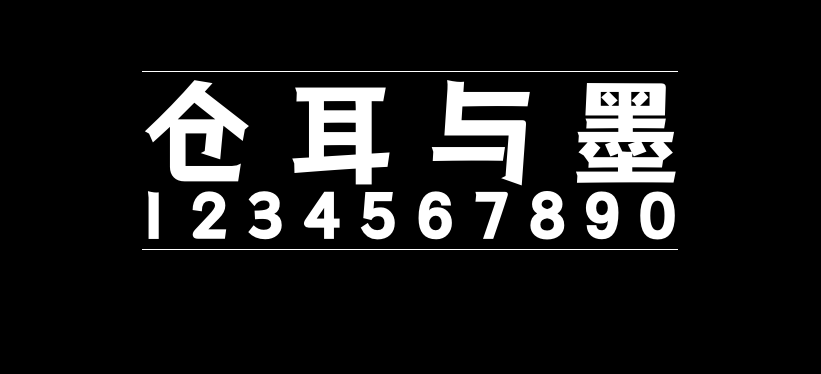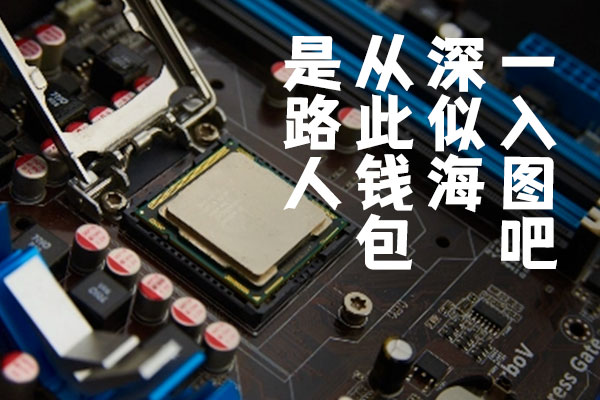
仓耳与墨
仓耳与墨(TsangerYuMo)是仓耳字库推出的一款免费字体,该字体包含5个字重,风格偏向现代创意字体,强调厚重与力量,具有醒目、有力和前卫的特点。
字体将篆刻的“刀意”融入其中,在笔形处理时模拟了类似篆刻的刀刻痕迹,同时为中和这种“尖锐”,在转折和“口”字结构上使用圆转角的处理方法,让整个字内方外圆。配套使用的英文和标点部分也同步沿用了与中文相同的设计特点,在混排时风格统一,不会突兀。
字数:本字体基于中华人民共和国GB2312-80字符集汉字部分标准,